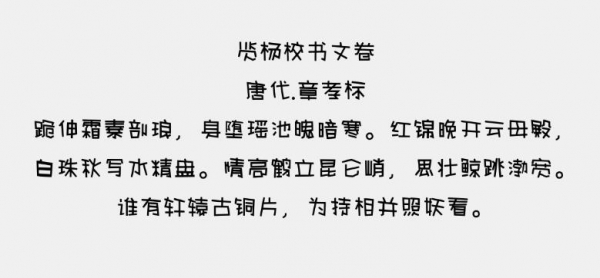
邯鄲萱萱簡(jiǎn)體是一款非常不錯(cuò)的藝術(shù)字體,工整簡(jiǎn)潔,具有強(qiáng)烈的視覺沖擊力,適應(yīng)于報(bào)紙和雜志和書籍中常用字體, 海報(bào)、個(gè)性促進(jìn)品牌標(biāo)志設(shè)計(jì)、字體設(shè)計(jì)、等環(huán)境使用,歡迎喜歡的朋友前來下載使用。